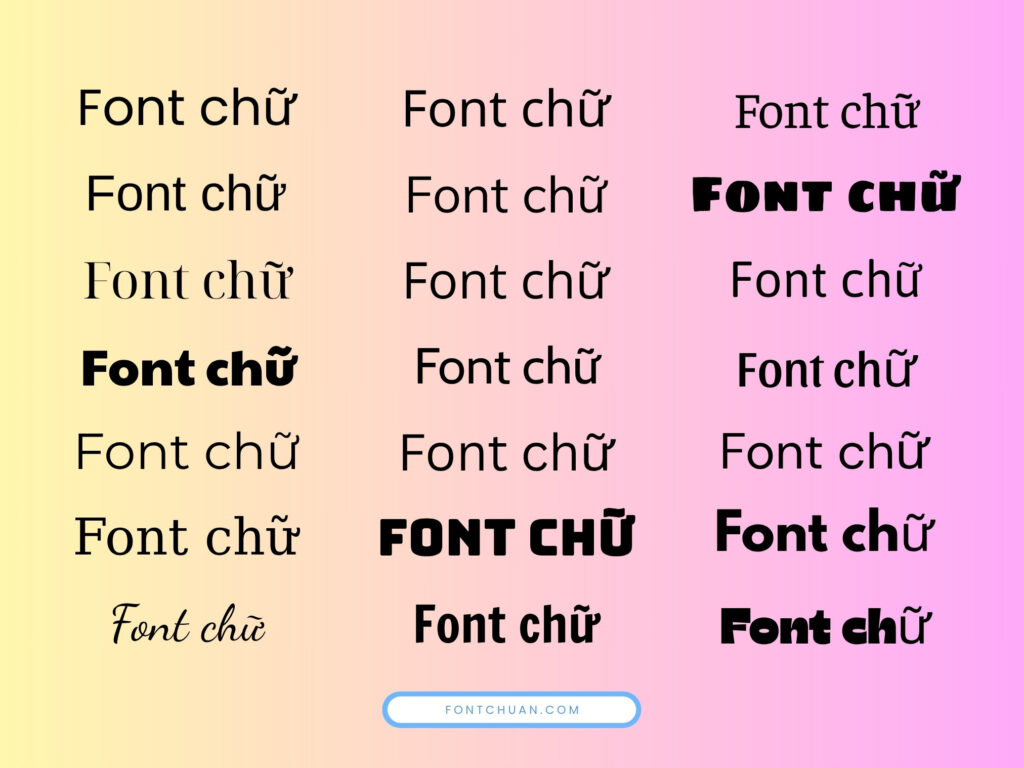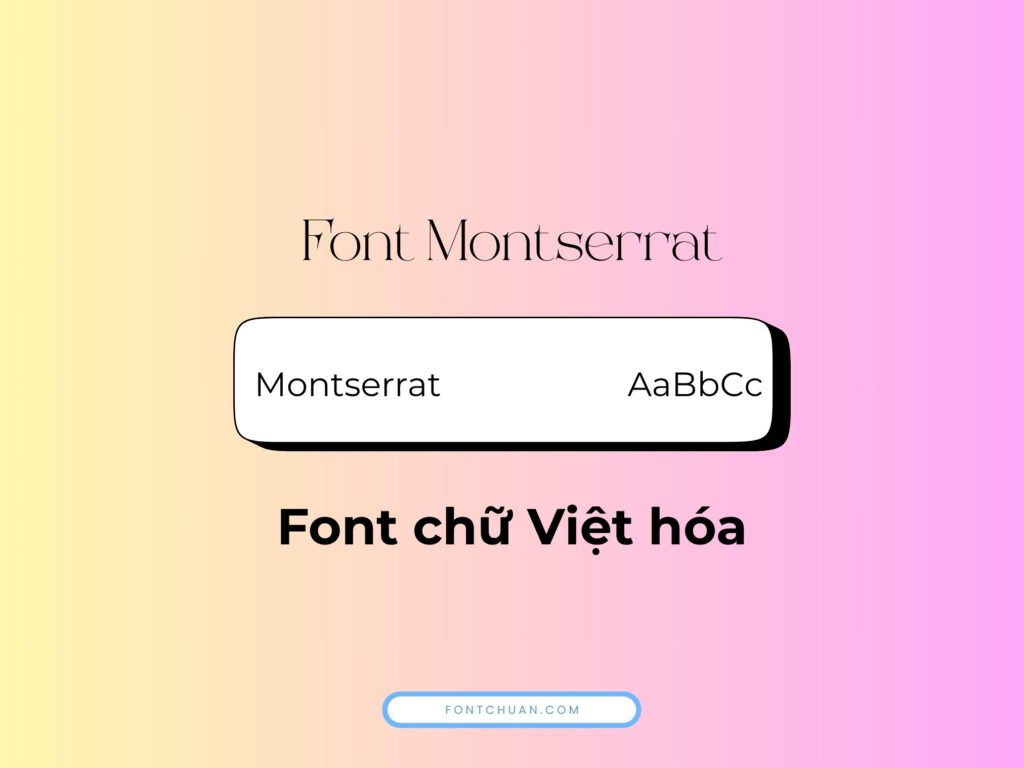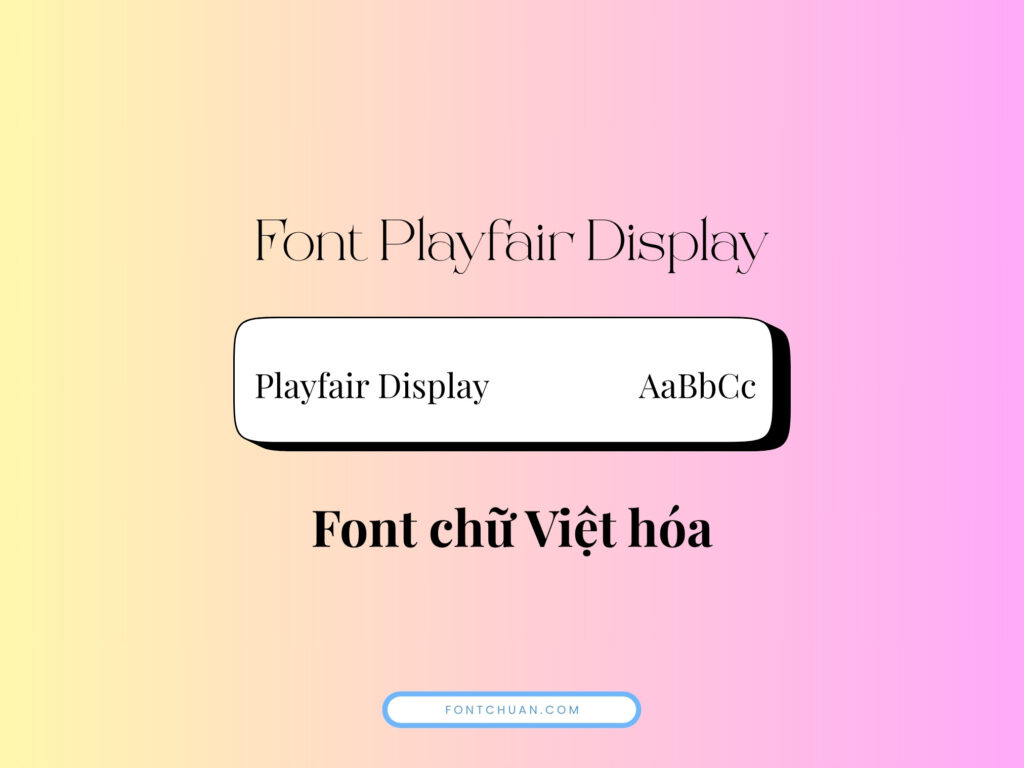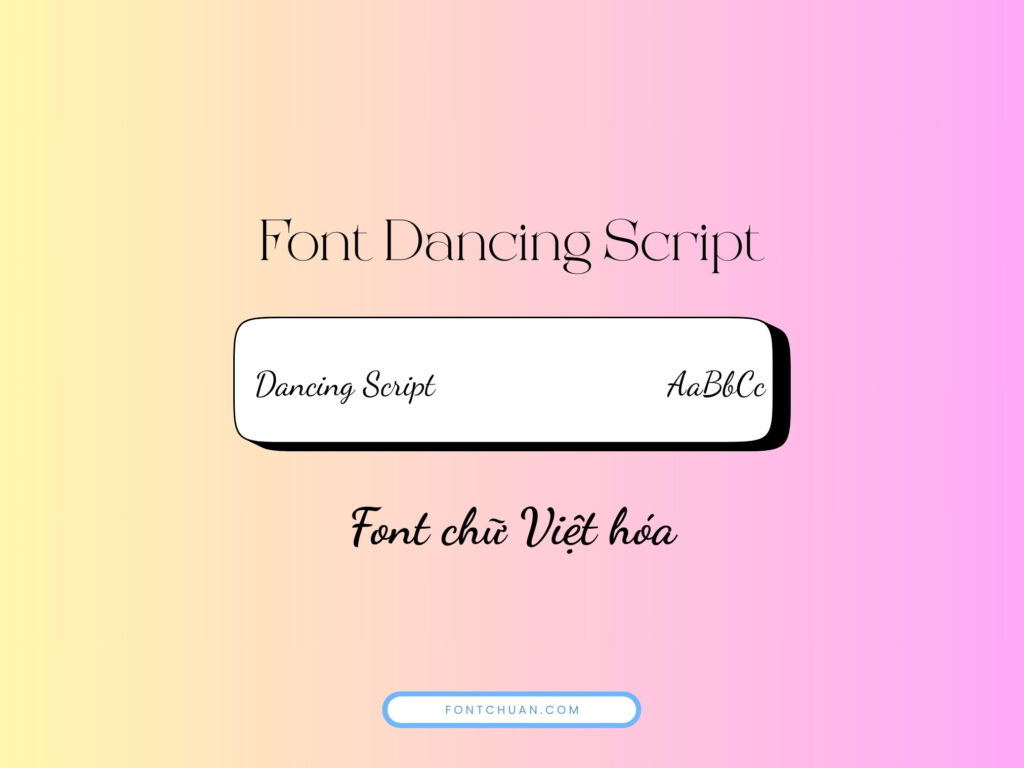
Việc sử dụng font Việt hóa trên Canva góp phần nâng cao tính sáng tạo và thẩm mỹ cho mọi thiết kế. Với đa dạng lựa chọn font chữ hỗ trợ đầy đủ dấu tiếng Việt, người dùng dễ dàng tìm thấy phong cách chữ phù hợp cho nhiều loại dự án khác nhau. Trong bài viết này, Font Chuẩn sẽ giới thiệu tổng hợp những font Việt hóa trên Canva được ưa chuộng nhất, giúp bạn tối ưu hóa trải nghiệm thiết kế một cách hiệu quả và chuyên nghiệp.
Tầm quan trọng của Font chữ Việt Hóa Canva
Canva giúp hàng triệu người Việt thiết kế ấn phẩm chuyên nghiệp mà không cần kỹ năng đồ họa chuyên sâu. Tuy nhiên, khi dùng tiếng Việt, nhiều font gốc thiếu ký tự có dấu, dẫn tới lỗi “ô vuông” hoặc dấu sai vị trí. Font Việt hóa – các bộ chữ đã bổ sung đầy đủ ă, â, ê, ô, ư, đ cùng năm dấu thanh – giải quyết triệt để vấn đề này, đồng thời giữ nguyên vẻ đẹp gốc của typeface.
Tại sao cần sử dụng Font Việt Hóa Canva
Việc lựa chọn và sử dụng font chữ phù hợp là yếu tố then chốt quyết định sự thành công của một thiết kế, đặc biệt khi nội dung hướng đến người dùng Việt Nam.
Hiển thị chính xác tiếng Việt, tránh gặp lỗi
Phần lớn font mặc định trên Canva chỉ hỗ trợ bảng ký tự Latin cơ bản. Khi gõ ă, â, ê, ô, ơ, ư hoặc đặt dấu thanh, chữ dễ biến thành ô trống. Font Việt hóa Canva đã bổ sung đầy đủ glyph Unicode cho tiếng Việt, bảo đảm văn bản hiển thị trọn vẹn và liền mạch.
Tăng tính chuyên nghiệp và thẩm mỹ
Các bộ font Việt hóa uy tín được tinh chỉnh chiều cao chữ, khoảng cách ký tự và vị trí dấu thanh để giữ nguyên vẻ đẹp gốc. Nhờ đó, thiết kế trông chỉn chu, giảm cảm giác “lệch dấu” và tạo ấn tượng chuyên nghiệp cho thương hiệu.
Cải thiện trải nghiệm đọc và mức độ tương tác
Khi nội dung dễ đọc, người xem tập trung vào thông điệp thay vì “giải mã” chữ lỗi. Điều này kéo dài thời gian ở lại trang, tăng tỷ lệ chia sẻ và góp phần cải thiện các chỉ số SEO on-page như dwell time và engagement.
Khẳng định bản sắc thương hiệu Việt
Font Việt hóa Canva mang lại nhiều phong cách: sans-serif hiện đại như Be Vietnam, Inter; script mềm mại như Great Vibes, Pacifico. Việc dùng kiểu chữ phù hợp giúp thương hiệu gần gũi và đáng tin cậy hơn với khách hàng trong nước, đồng thời vẫn giữ trải nghiệm nhất quán cho người dùng quốc tế.
Giới thiệu các font Việt hóa của Canva được sử dụng nhiều nhất
Để giúp người dùng dễ dàng lựa chọn font phù hợp, dưới đây là danh sách các font Việt hóa phổ biến trên Canva, được phân theo phong cách thiết kế và ứng dụng thực tế.
Font Sans Serif Việt Hóa Canva
Font Sans Serif mang phong cách tối giản, dễ đọc, phù hợp với thiết kế kỹ thuật số, slide thuyết trình, banner, và website. Một số font nổi bật:
- Open Sans: Dễ đọc, thân thiện, phù hợp cho mọi thiết kế.
- Montserrat: Hiện đại, rõ ràng, lý tưởng cho branding và thời trang.
- Roboto: Kết hợp hình học và mềm mại, hiển thị tốt trên mọi nền tảng.
- Nunito: Nhẹ nhàng, trung tính, phù hợp với app, web.
- Quicksand: Tròn trịa, trẻ trung, mang cảm giác vui tươi.
- DM Sans, Varela Round, Duru Sans, Be Vietnam Pro: Linh hoạt, hỗ trợ tiếng Việt tốt, ứng dụng rộng rãi.
Font Canva Serif Việt Hóa
Font Serif có chân, tạo cảm giác nghiêm túc và truyền thống, thường dùng cho sách, tạp chí, website tin tức. Gợi ý:
- Lora: Kết hợp cổ điển và hiện đại, lý tưởng cho văn bản dài.
- Playfair Display: Thanh lịch, sang trọng, phù hợp cho tiêu đề blog và thiết kế thời trang.
- Merriweather: Tối ưu cho màn hình, phù hợp với nội dung dài.
- Bon Foyage: Serif thư pháp hiện đại, ứng dụng trong logo, lời mời, thiệp cưới.
Font chữ thư pháp Việt hóa Canva
Font mô phỏng chữ viết tay, mang phong cách mềm mại và nghệ thuật, thường dùng trong thiệp cưới, sự kiện, poster. Gợi ý:
- Pacifico, Charmonman, Dancing Script: Thân thiện, uyển chuyển.
- Bellissima Script Pro, Parfumerie Script, Bilgate: Tinh tế, phù hợp với thiệp mời cao cấp.
- iCiel Thư Pháp, Utm Thư Pháp: Đậm chất truyền thống Việt, lý tưởng cho thiết kế Tết.
- SVN-TheUntold Story, Smooch, Shintia Script: Viết tay vui nhộn, cá tính.